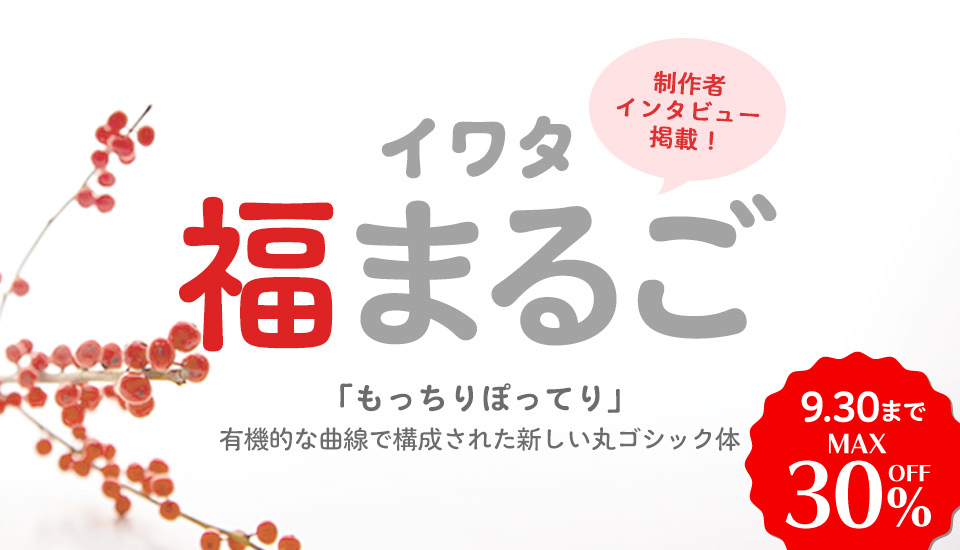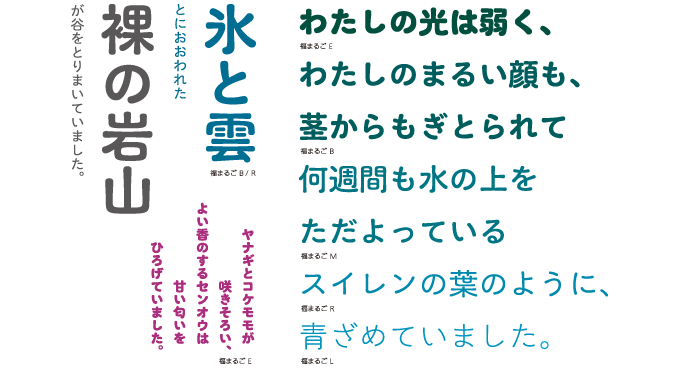
イワタ 福まるご
「もっちりぽってり」今までにない新しい丸ゴシック体の誕生
有機的な曲線で構成された、これまでにないシルエットの丸ゴシック体です。ノーマルな丸ゴシックでは物足りないが、ポップ書体では強すぎる、そんなときの新しい選択肢になれる書体。見出しから、しっかり文字組までこなせます。
イワタ福まるご とは
個性的なエレメントをもちながら骨格は奇をてらわずベーシックであることで、親しみやすいのに見たことのない表情の丸ゴシック体です。構想に2年半、制作に4年と、計6年以上をかけて、今までにない新しい丸ゴシック体として2020年3月に発売されました。
イワタ福まるごの特徴
現代のデジタルフォントでも活字の雰囲気を表すために「低めの重心」と「ユニークな丸み」がある新しい丸ゴシック体です。細~中間のウエイトは長文にも適した読みやすさがあり、太いウエイトはふっくらと豊かな丸みを活かした目を惹くデザインです。
丸ゴシックと言っても単に先端や転折部が丸いだけではなく、1画1画に太細の抑揚があり、口のパーツは外側にふっくらな広がりなど、単純な直線が極力生じないのも特徴です。エレメントで特徴的なのは、短くぐっとこらえたようなハネや、起筆を細く終筆を太くし強弱をつけた短めの点です。
イワタ福まるご 書体の特徴 イワタ福まるご 書体見本
イワタ福まるご L/R/M/B/E
有機的な曲線で構成された、これまでにないシルエットの丸ゴシック体。「もっちりぽってり」。見出しから、しっかり文字組までこなせます。
オススメの使い方
インタビュー
デザインポケットでは、「イワタ福まるご」の制作にかかわった同社デザイン部にお話を伺いました。
── 誕生のきっかけ、影響を受けたもの
本多が入社間もない頃、イワタの前身である岩田母型の活字見本帳を整理をする中で、一風変わった丸ゴシックに出会いました。
ちょっと不格好にもみえる骨格と優しい丸さがかわいらしく、一目惚れしたのが始まりです。
関連資料がないか、タケノコ・デザインルームの竹下氏 (以下、竹下氏) に相談したところ、森川龍文堂 (代表の森川健市は、のちの岩田母型の大阪支店長) の見本帳を紹介してもらいました。
こちらには太い見出し書体もあり、これらの特徴を掛け合わせたファミリー展開での制作を提案しました。
また、イワタにはオールドスタイルの明朝と角ゴシックはありましたが、丸ゴシックはなかったため、そのことも制作の後押しとなっています。
── 書体名の由来
初めてお披露目した展示会でノベルティにぽち袋をつくった際、書体の特徴がわかる「福」の字をデザインに盛りこみました。
ポジティブな言葉であり「ふくまるご」という音の響きもよいことから、それが書体名にも採用されました。
見た目の印象もやわらかく「まるご」はひらがな表記にしています。
── 構想から制作まで
2013年に見本帳を見つけてから水面下で試作を進めつつ、本格的に始動したのが2016年の1月です。
構想に2年半、制作に4年と、計6年以上かかっています。
── 複数ウェイトの制作
はじめから複数ウェイトの開発を想定していたため、太いウェイトと細いウェイトを同時に着手しました。
まずは見本帳の太さを参考にし、そこから社内の他の書体との比較を重ね、現在のLからEの5ウェイトに落ち着きました。
── 制作メンバーと作業分担
見本帳の相談をしたところから竹下氏が加わり、本多のスケッチを元に竹下氏と意見を出し合いながら基本的なエレメントを作り込むという流れで進めました。
デザインの方向性が決まると基本漢字の約400字を2名で分担して作成、2017年から坂口も加わり、3名で必要字種の一式を揃えました。
── 一番のこだわりのポイント
【書体全体のデザインの特徴】
現代のデジタルフォントで元となる活字の雰囲気を表すために「低めの重心」と「ユニークな丸み」を活かすことに重点を置き、とくに後者の表現に注力しています。
丸ゴシックと言っても単に先端や転折部が丸いだけではなく、1画1画に太細の抑揚をつけ、口のパーツは外側にふっくら広げるなど、単純な直線が極力生じないようにしています。
イワタ福まるご 見本帳/初期デザイン/最終デザイン
また、起筆や収筆が他の線と接する場合にも、インクにじみのようなわずかなカーブをつけています。
エレメントで特徴的なのは、短くぐっとこらえたようなハネや、起筆を細く終筆を太くし強弱をつけた短めの点です。
このような個性的なエレメントをもちながら骨格は奇をてらわずベーシックであることで、親しみやすいのに今までにない表情の丸ゴシックに仕上がっています。
イワタ福まるご 見本帳/初期デザイン/最終デザイン
【漢字 かなカナ 英数字の字面や骨格・エレメントの特徴】
先に挙げた以外では、口は外に膨らんでいるのに対し「円」や「月」などはウエストをくびれさせメリハリをつけています。
基本的なこととしては、LからEの太さにかなり幅があるので、細いウェイトほど字面を小さくする、重心や点画のバランスを揃えるなど、5ウェイトがきちんと1つのファミリーに見えるよう配慮しています。
イワタ福まるご L,R,M,B,E
ひらがなやカタカナはオールド系ということもあり小ぶりに設計しました。骨格は漢字と同様に、本文にも耐えうる汎用性のあるデザインを意識しています。
その骨格を決めるところから新規に書き起こしていますが、カタカナの「ロ」の下部を少しすぼめる、「ホ」の縦画をハネないなど、活字の味も加えています。
欧文も一から起こし、手書き感がありながら使いやすいものを目指しました。例えば、先端の抑揚が均一では弱く感じたので、Lの収筆や小文字の縦画などを斜めにして動きを出しています。
ささやかなこだわりとしては、坂口が手がけた天気マークを5ウェイト並べてみてほしいです。
イワタ福まるご 天気マーク
── 制作で一番苦労したところ
本書体の特徴である線の抑揚とハネの形状です。
抑揚は弱いと見えず、強いと墨だまりのようになってしまいます。太いウェイトで画数の多い字では、抑揚を強調しながらも隙間が埋もれすぎないような工夫が必要でした。
思い切った短いハネは元の見本帳内では長さが様々で、どのあたりのイメージに近づけるか、今のデザインに落ち着くまで試行錯誤がありました。
── 特徴が一番引き出せる一文字
よく聞かれますが選ぶのは難しいです。線の込み入った字でも「一」でも福まるごだとわかります。
強いて言えば「山」「見」「力」などのシンプルな字ほどエレメントの特徴がわかりやすいと思います。
イワタ福まるご シンプルな字の例
── 使ってほしい・想定している利用用途
ポスターやパッケージなどの目を惹く見出しはもちろん、細いウェイトは長文での可読性もあり、幅広い活躍を期待しています。全てのウェイトに抑揚が効いているので、細いウェイトを大きく使っても他の書体との違いがでて面白いかもしれません。
ノーマルな丸ゴシックでは物足りないが、ポップ書体では強すぎる、そんなときの新しい選択肢になれる書体ではないでしょうか。
イワタ福まるご 使用例
本多 育実 (左)
1990年 東京生まれ 埼玉育ち
2013年 武蔵野美術大学 造形学部 視覚伝達デザイン学科卒業
坂口 ゆかり (右)
1994年 和歌山県出身
2017年 京都精華大学 デザイン学部 ビジュアルデザイン学科卒業
同年 株式会社イワタ入社 デザイン部所属
竹下 直幸 (中央)
タケノコ・デザインルーム
「竹」「イワタUD新聞明朝」「みんなの文字」などをデザイン